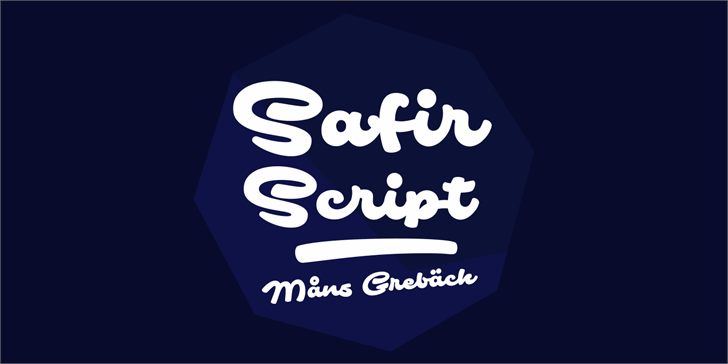
Safir Script é uma fonte de estilo calligrafia criada pelo designer Hamilton, oferecendo um tom elegante e sofisticado que se adequa perfeitamente para qualquer projeto de design gráfico. Esta fonte não apenas adicionará um toque especial às suas criações digitais, mas também trará uma personalidade única aos textos de sua página web ou site. Com seus traços fluidos e acabamentos delicados, Safir Script é ideal para elementos de design que exigem um ar de elegância. Suas formas curvilíneas e detalhes finos são perfeitos para gráficos publicitários, editoriais de moda ou até mesmo revistas internacionais que buscam uma impressão sofisticada. Estamos entusiasmados em apresentar a Safir Script à comunidade de designers. Se você está procurando por um recurso gráfico elegante e versátil para seus projetos comerciais, não hesite em visitar nosso site para explorar mais detalhes sobre o uso desta fonte única.